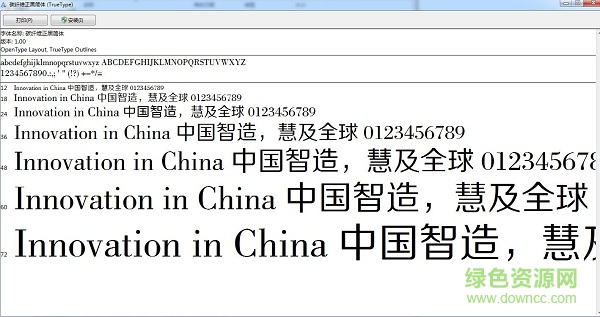
txwzhjw gb1 0是什么字體?txwzhjw gb1 0字體就是碳纖維正黑簡(jiǎn)體,該字體保持了黑體的基本特點(diǎn),筆畫棱角分明,字形挺拔端正,有需要的小伙伴快來(lái)本站免費(fèi)下載吧!
漢字的黑體是在現(xiàn)代印刷術(shù)傳入東方后依據(jù)西文無(wú)襯線體中的黑體所創(chuàng)造的。由于漢字筆劃多,小字黑體清晰度較差,所以一開(kāi)始主要用于文章標(biāo)題。但隨著制字技術(shù)的精進(jìn),已有許多適用于正文的黑體字型。
這個(gè)詞的范疇和無(wú)襯線字體(Sans-serif)是類似的。所以在中文字體中常用“黑體”,在西文中常用“無(wú)襯線體”的稱呼。而宋體就可以被稱作襯線字體。 “黑體”在日文中被稱為Goshikku-tai(直譯即“哥特體”)。